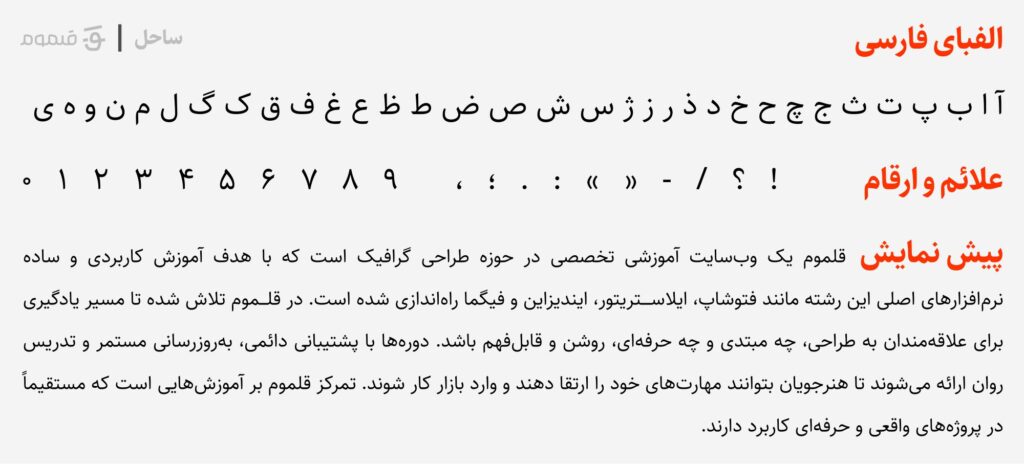
خانواده فونت ساحل
Sahel
فونت ساحل یکی دیگر از فونت‌های رایگان و متن‌باز فارسی است که توسط صابر راستی‌کردار طراحی شده. این فونت در ۶ وزن مختلف منتشر شده و ظاهر آن نسبت به وزیر کمی جمع‌وجورتر و فشرده‌تر است. به همین دلیل برای متن‌هایی که نیاز به اشغال فضای کمتر دارند (مانند رابط کاربری اپلیکیشن‌ها یا جداول و ستون‌های باریک وب‌سایت) انتخابی کاربردی به شمار می‌رود.
ساحل به خاطر سادگی، روانی و هماهنگی مناسب با فونت‌های لاتین، یکی از گزینه‌های محبوب طراحان وب و اپلیکیشن است. اگر به دنبال فونتی هستید که در عین خوانایی، ظاهر مدرن و کم‌حجم هم داشته باشد، ساحل می‌تواند انتخاب هوشمندانه‌ای باشد.